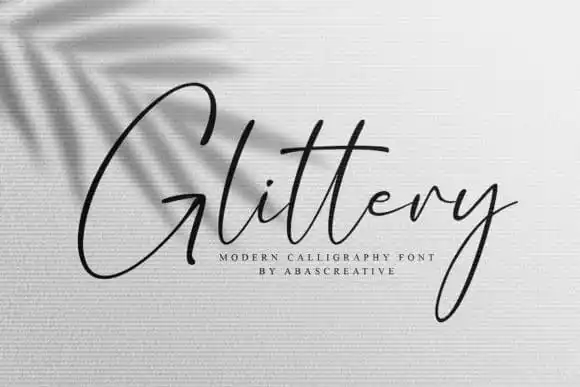
Glittery Script Font – Download Grátis
A Glittery Script Font é uma fonte script elegante criada por AbasCreative. Ela traz a sofisticação e a simplicidade do estilo natural de assinatura, com suas linhas reticentes criadas para dar um toque romântico e moderno. Ideal para aplicações como marca, assinaturas, convites de casamento, promoções, embalagens de produtos e muito mais ideias que precisam de uma pitada de glamour e elegância. Com o Glittery Script Font, você pode tornar qualquer projeto um pouco mais especial e chamativo.